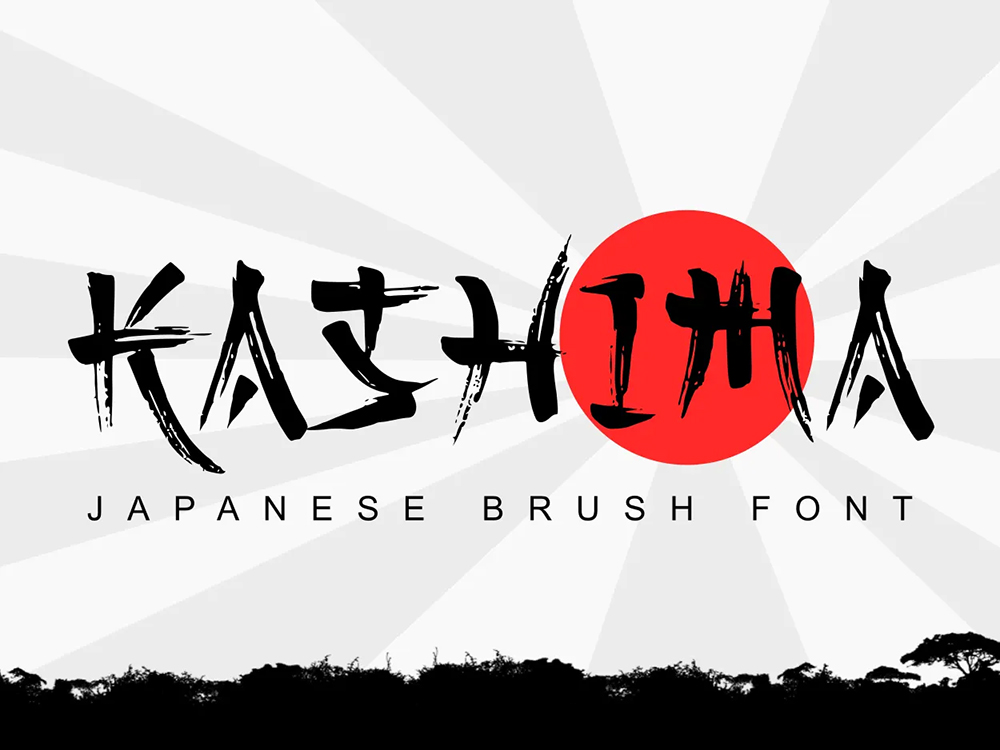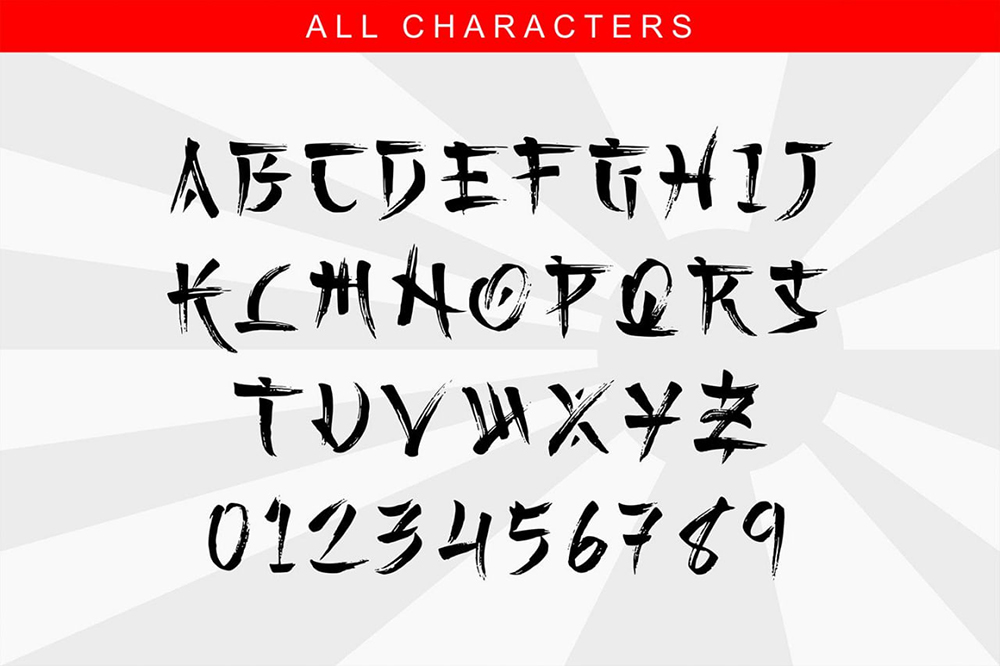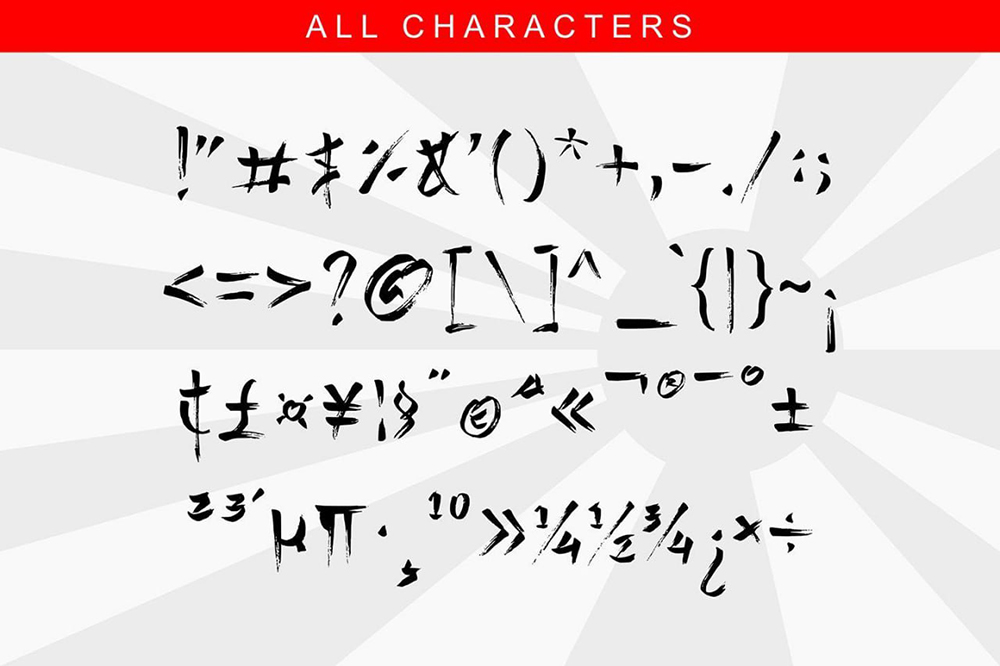
فونت پرمیوم و انگلیسی Kashima Font يک فونت قلممو با سبک ژاپنی است که با استفاده از قلممو واقعی ساخته شده است. اين فونت برای پوشاک، برندسازی، لوگو، مجله، نقل قولها، بستهبندی، تبليغات و… عالی است. Kashima با حروف بزرگ، علائم نگارشی، نمادها و اعداد نوشته شده است و چندزبانگی پشتيبانی میکند.